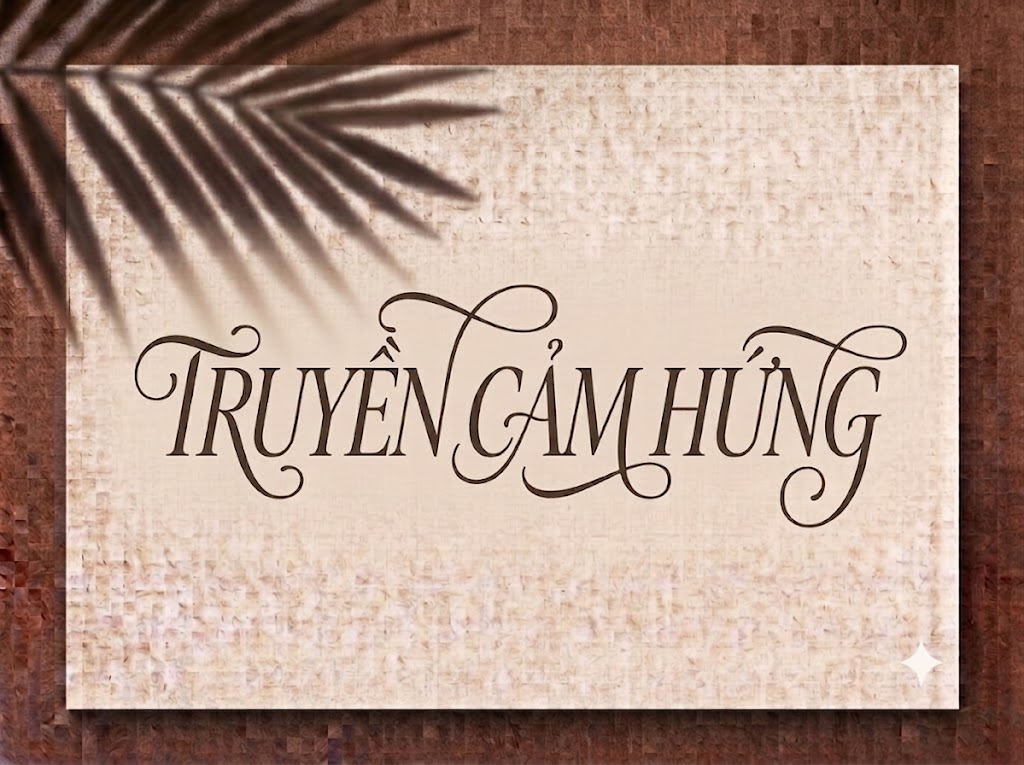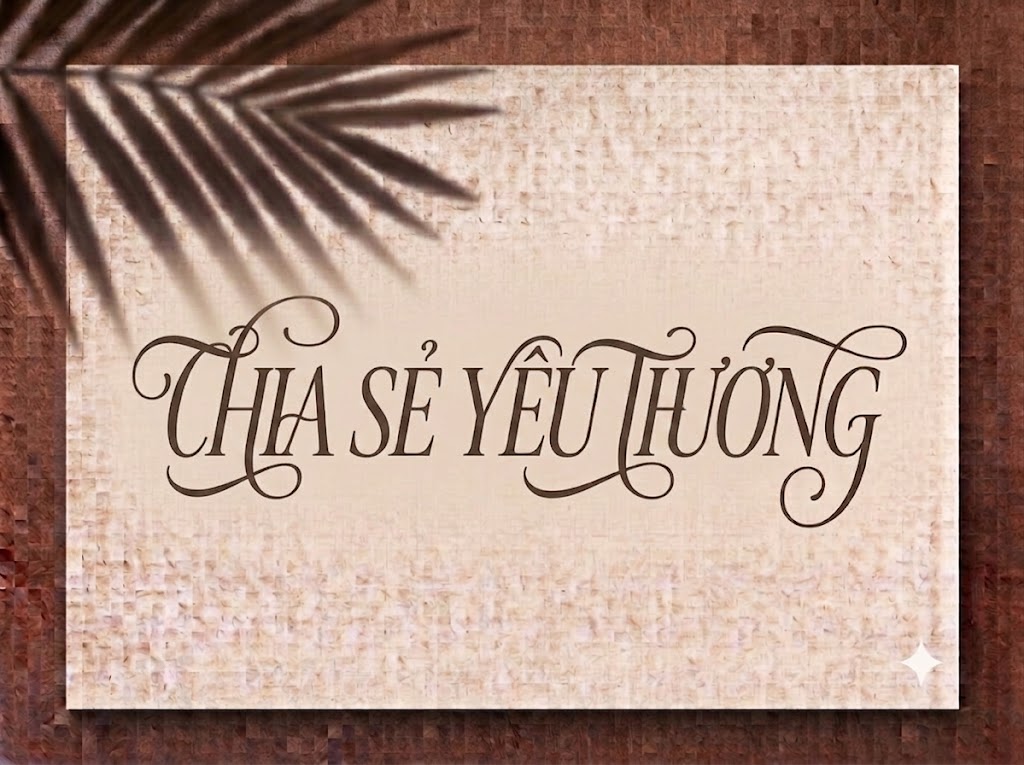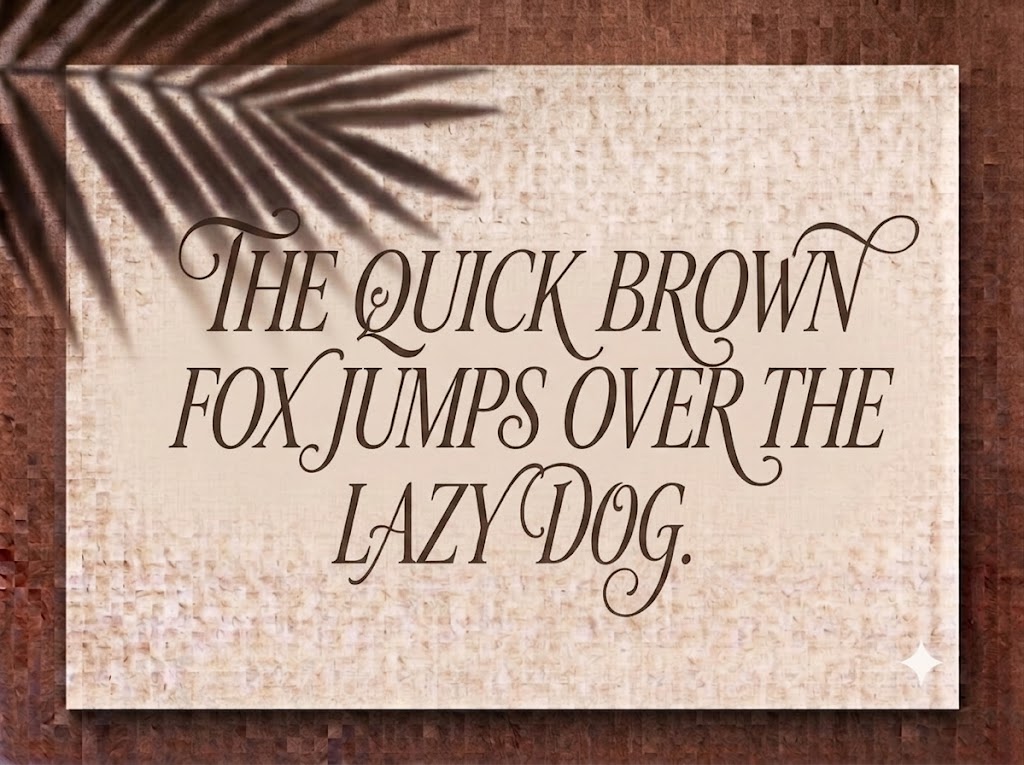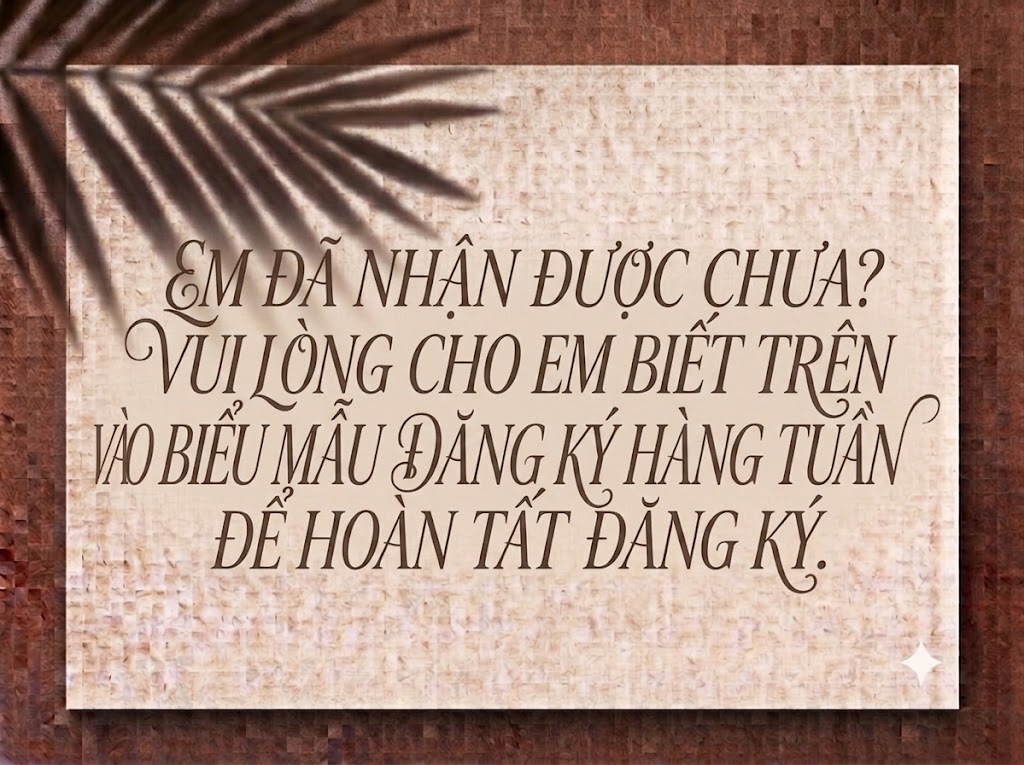
1FTV La Graziela
Trong nghệ thuật chữ viết, dòng phông chữ Calligraphy (thư pháp phương Tây) với những đường nét bo cong uốn lượn luôn mang lại sự mềm mại, tinh tế và vẻ đẹp kiều diễm tuyệt đối. Một dòng tiêu đề thư pháp được chăm chút kỹ lưỡng không chỉ truyền tải thông điệp mà còn thổi vào ấn phẩm chất nghệ thuật bay bổng và đầy cảm xúc.
Nếu bạn đang tìm kiếm một phông chữ thư pháp cao cấp với các ký tự in hoa bay bổng để làm thiệp cưới, nhận diện thương hiệu thời trang hay tiêu đề video ngắn, font 1FTV La Graziela chính là sự lựa chọn không thể bỏ qua.
Giới thiệu về font 1FTV La Graziela
Font 1FTV La Graziela là bộ chữ hiển thị phong cách Calligraphy cổ điển kết hợp hơi thở hiện đại, nổi bật với sự uyển chuyển giữa các nét nối và các ký tự viết hoa được tạo hình cầu kỳ:
Tên phông chữ: 1FTV La Graziela
Đặc điểm nổi bật của phong cách thiết kế La Graziela
Sức hút thị giác của font 1FTV La Graziela đến từ nét vẽ hoa mỹ và nhịp điệu mềm mại trong từng nét chữ:
Ký tự in hoa bay bổng nghệ thuật: Các chữ cái viết hoa được tạo hình với các đường nét gợn sóng và vòng uốn (swash) cầu kỳ, tạo nét nhấn quý phái ngay từ ánh nhìn đầu tiên.
Dáng chữ nghiêng mềm mại: Bộ chữ cái viết thường được nối nét tự nhiên, có độ nghiêng thanh thoát giúp câu văn chảy mượt như nét bút nét mực thực sự.
Dãy chữ số nghiêng đồng bộ: Hệ thống chữ số từ 0-9 cũng được thiết kế theo phom dáng nghiêng mềm mại, ăn nhập hoàn hảo với tổng thể bộ phông chữ.
Khoảng cách giữa các chữ (kerning) và điểm nối nét được tính toán chuẩn xác, giúp các ký tự khi ghép lại thành từ luôn giữ được sự liên kết mượt mà, không bị hẫng hay dính nét.
Tích hợp trọn vẹn bộ chữ cái hoa – thường, dãy chữ số cùng hệ thống ký tự đặc biệt, dấu câu thông dụng.
Bản Việt hóa chuẩn chỉnh giúp bạn hoàn toàn yên tâm thiết kế các văn bản tiếng Việt có dấu mà không gặp lỗi nhảy font hay mất ký tự.
Hình ảnh demo thực tế của font 1FTV La Graziela
Khả năng hiển thị của phông chữ này được tối ưu tốt trên nhiều tỷ lệ kích thước:
Kích thước nhỏ (12pt – 24pt): Cấu trúc chữ nghiêng và đường nét mềm mại giúp các dòng chữ nhỏ vẫn hiển thị rõ ràng, thanh mảnh trên màn hình di động.
Kích thước lớn (36pt – 72pt): Đây là đất diễn lý tưởng nhất để 1FTV La Graziela phô diễn toàn bộ sự kiêu sa, lộng lẫy của các đường uốn lượn ở chữ hoa, tạo tác động thị giác mạnh mẽ cho các dòng tiêu đề chính.
Ứng dụng trong thiết kế đồ họa và làm video
Sở hữu nét cá tính sang trọng và đầy tính nghệ thuật, font 1FTV La Graziela mở ra không gian ứng dụng phong phú:
Thiết kế thiệp cưới và sự kiện: Lựa chọn hàng đầu cho các mẫu thiệp cưới cao cấp, thiệp mời sự kiện VIP, menu tiệc sang trọng nhờ vẻ đẹp lãng mạn và quý phái.
Video ngắn (TikTok, Reels, Shorts): Phông chữ thư pháp mềm mại này hiển thị rất đẹp trên khung hình đứng tỷ lệ 9:16. Nó cực kỳ ăn nhập với các video vlog cưới, phong cách sống, review mỹ phẩm, trang sức hay thơ ca.
Ảnh thu nhỏ YouTube (Thumbnail): Lựa chọn tuyệt vời cho các kênh làm nội dung về âm nhạc lofi, acoustic, nhạc nhẹ chữa lành hoặc review đồ hiệu nhờ giao diện tinh tế và thu hút.